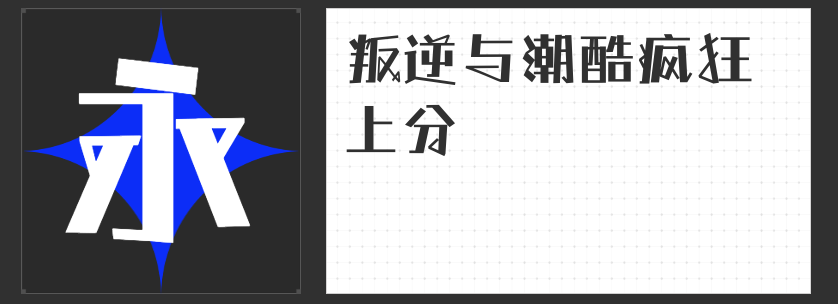
艺术海报中的视觉盛宴:四款独特字体推荐
在艺术海报的设计中,字体选择至关重要,它不仅传递信息,更是整体风格与氛围的塑造者。今天,就让我们一起探索四款专为艺术海报而生的独特字体,它们各具特色,定能为你的作品增添无限魅力。
1.字恋狂拙黑简
这款创意字体以其独特的笔画设计脱颖而出,整体上切口平直的纯直线笔画,横细竖粗,中宫宽博,重心平稳。连笔与连丝的设计,以及小部分笔画的手写化处理,让这款字体充满了叛逆感,年轻而潮酷,独特且与众不同。它非常适合用于表达个性鲜明、不拘一格的主题。
这款字体整体风格自由率真,活泼灵动。单字结构周正而不失松弛,点画圆润,笔画间粗细过渡自然,给人一种行云流水般的流畅感。灵动的笔画走势造就了其独特的字形风貌,非常适合用于展现自然、灵动、活泼的主题。
这款字体笔墨浓厚,粗细对比较为明显,字体结构中正,极具视觉冲击力。其中,“勾、提、挑、捺”等笔画特点明显且夸张,单字结构收放自如,展现出一种力量与美感并存的独特韵味。它非常适合用于表现力量、冒险、神秘等主题。
这款字体融合了圆体与黑体的特点,在笔画拐角增加了适当的外圆角,使得整体稳重大气的字形中增添了几分灵动。字体字面充实,结构稳定,更适配屏显使用。它非常适合用于传递坚定、有力、积极向上的信息。
这四款字体各具特色,无论是叛逆不羁的“字恋狂拙黑简”,还是灵动活泼的“造字侠醉春风简繁”,亦或是力量感十足的“造字侠伏魔简繁”,以及稳重大气的“励字志向黑简”,都能为你的艺术海报设计带来意想不到的惊喜。